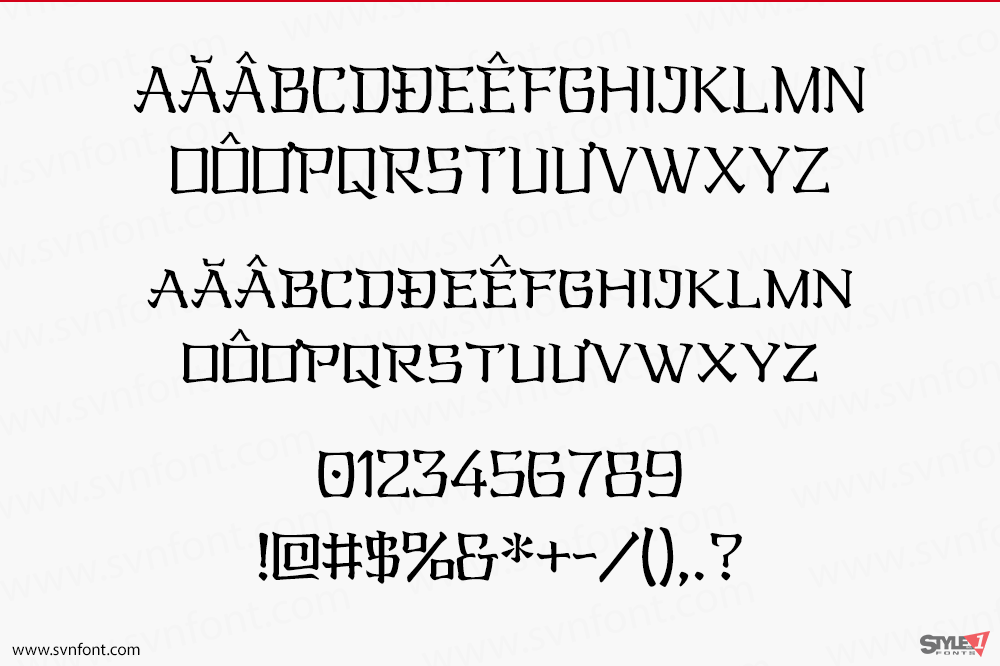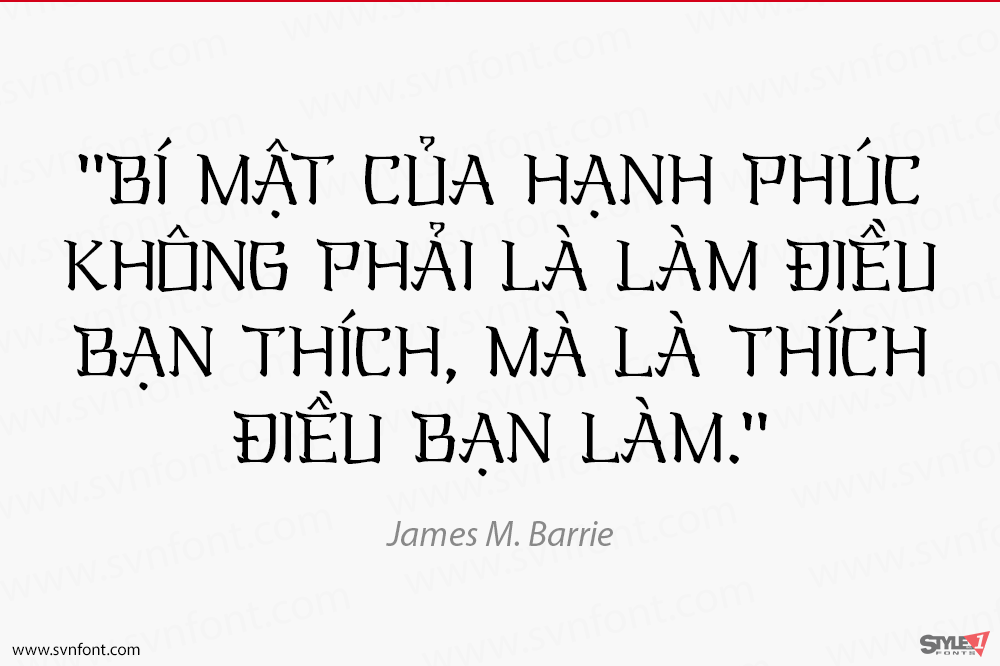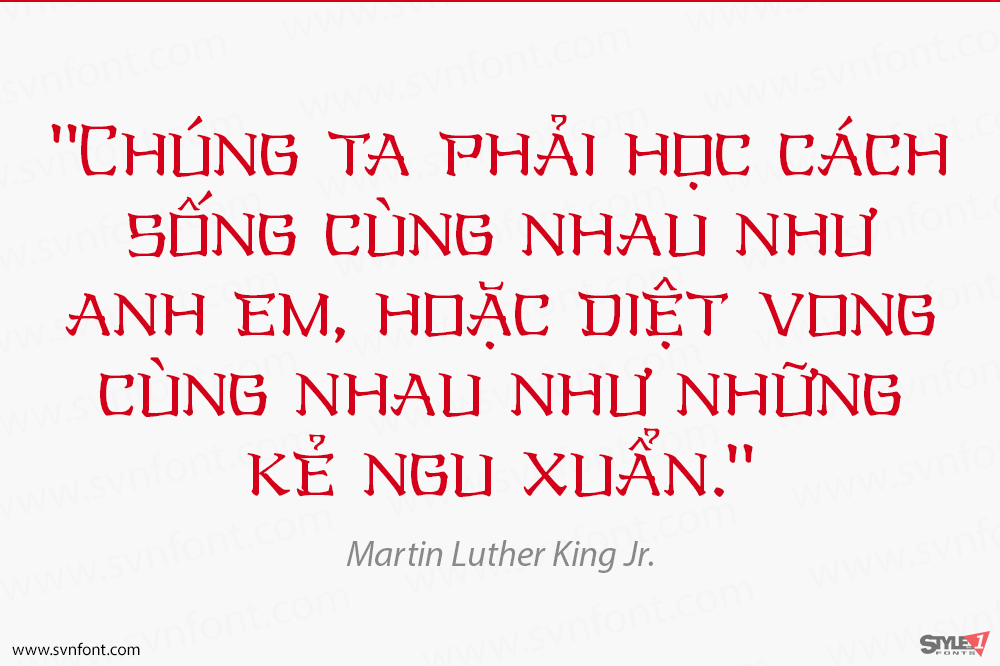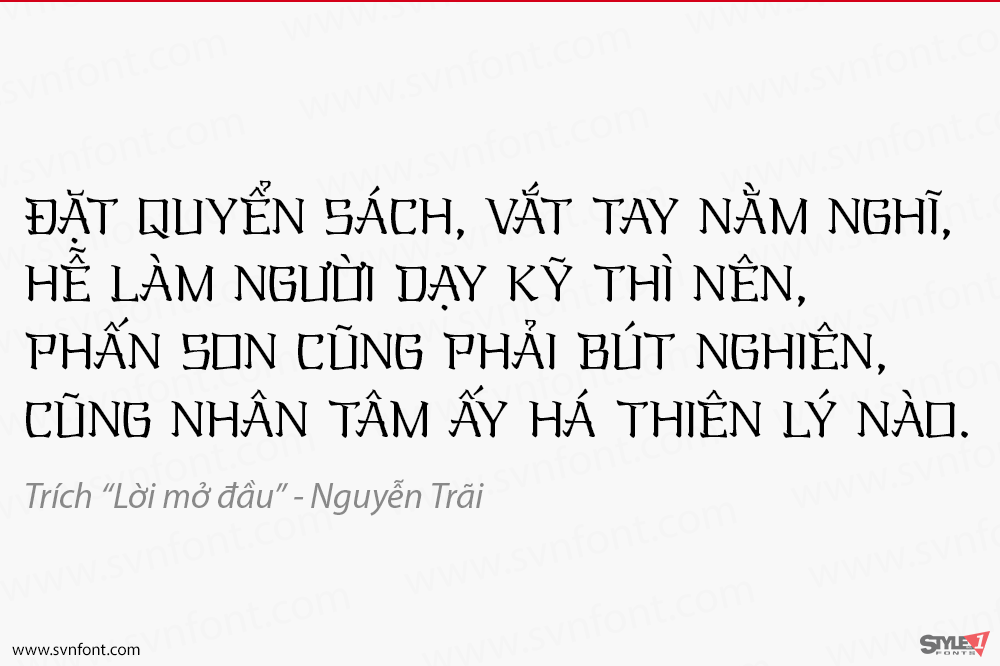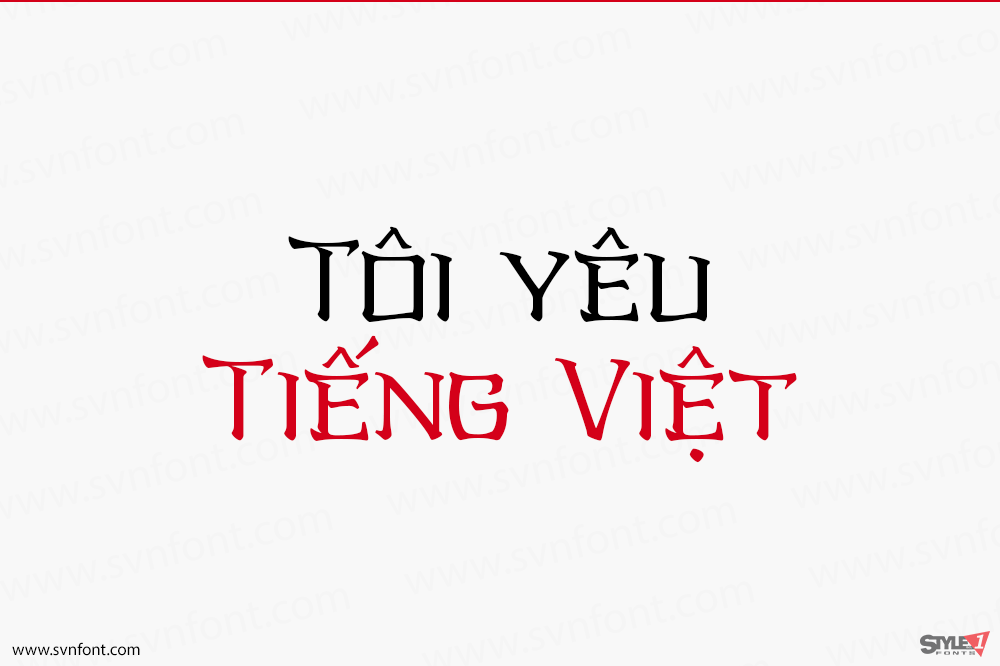
Oriental Kaishu, một font chữ được thiết kế giữ lại những tinh hoa đặc điểm của chữ Viết Trung – Nhật – Hàn. Font. Font thích hợp cho các thiết kế về chủ đề Văn hóa, ẩm thực, du lịch, bia sách – truyện… về các nước Á Đông.
Nhà thiết kế: Alexander Bobrov
Nhà phát hành: Indian Summer Studio